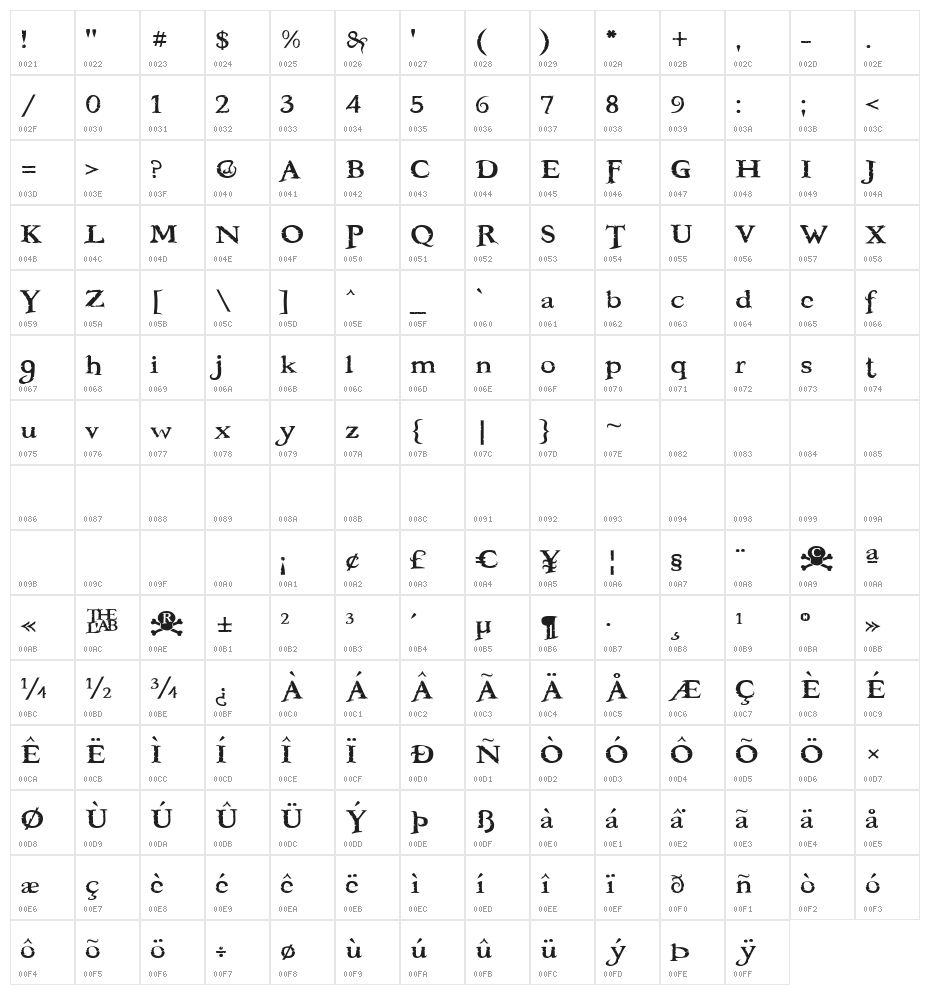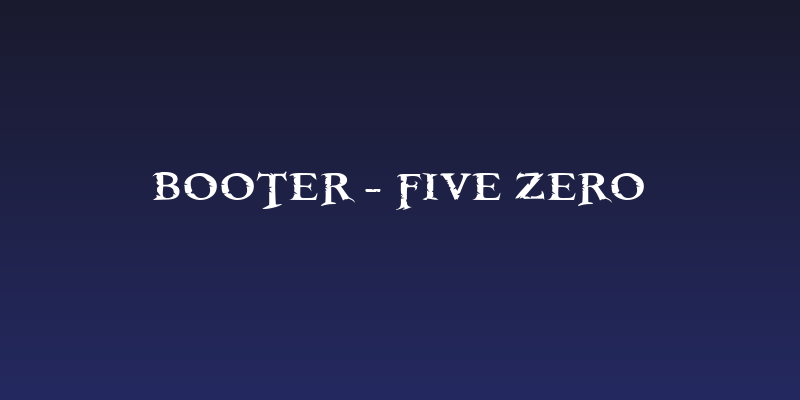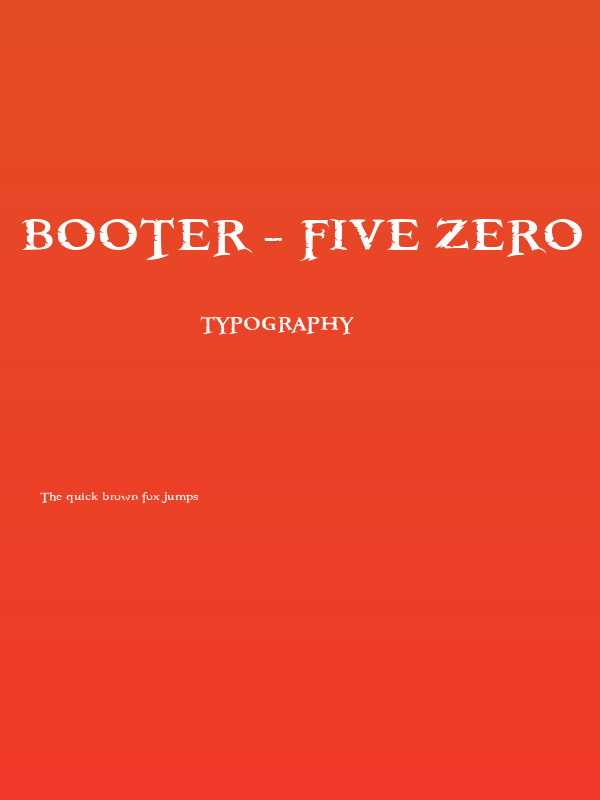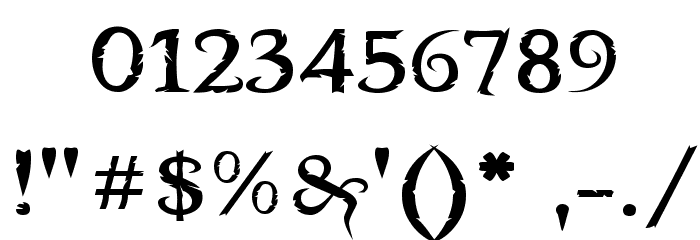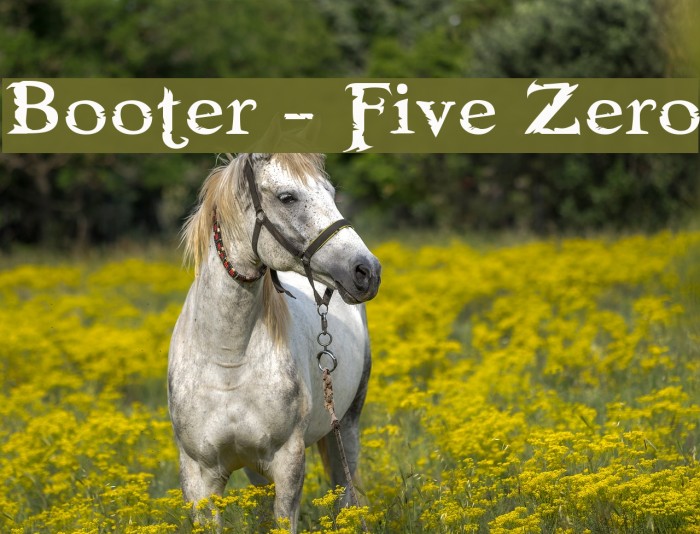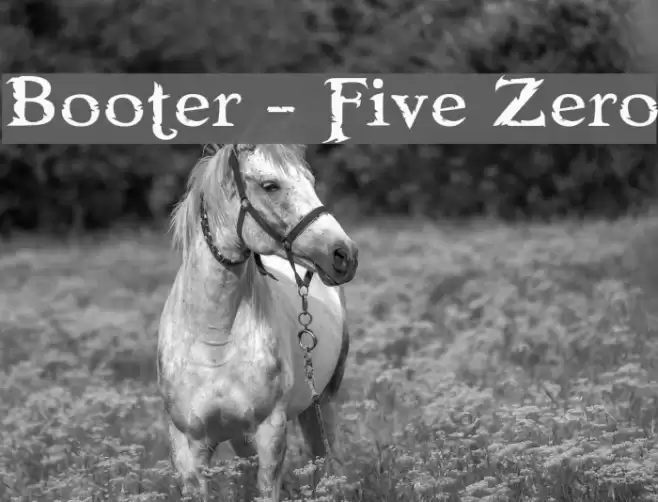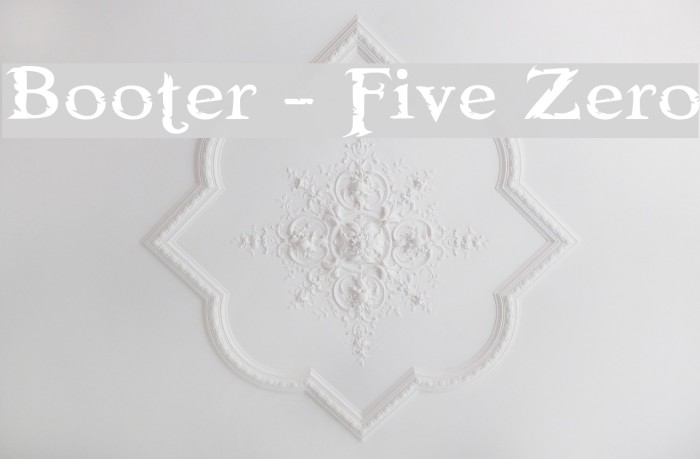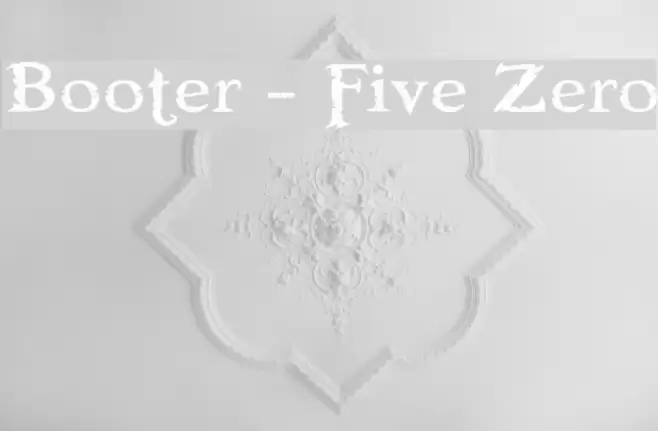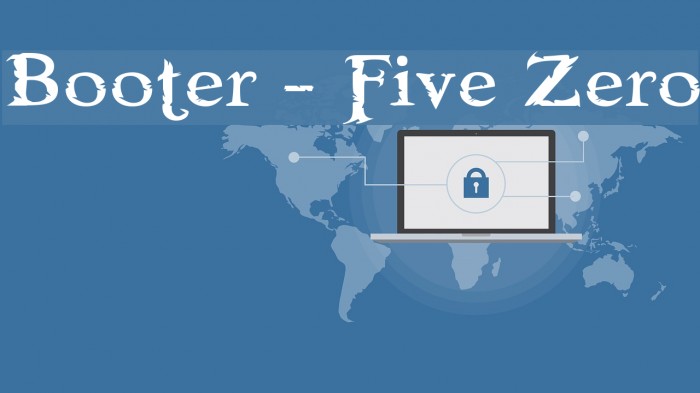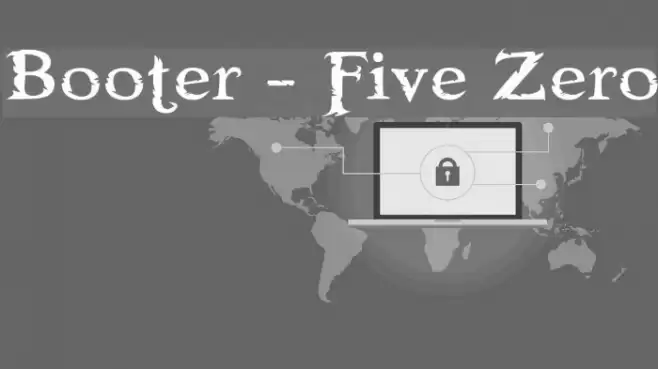
Booter - Five Zero Font
| Proiecte propuse | Ideal for horror-themed posters, edgy branding, or album covers that require a striking visual presence. |